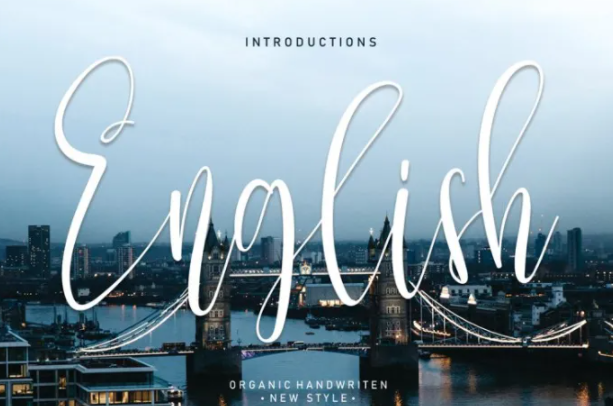
[Fontbundles] English Font (2021)
Популярный и профессиональный шрифт. Современный и элегантный, этот шрифт состоит из красивых креативных штрихов.
Этот шрифт идеально подходит для ваших творческих идей, как формальных, так и неформальных. Он имеет современный стиль с нотками творческих идей, который очень подходит для применения везде, где требуются творческие идеи, например, на пригласительных открытках,
бланки, логотипы сайтов, социальные сети, баннеры, реклама, брошюры, упаковочная продукция, кожаные изделия и любая продукция, требующая написания.
Благодаря использованию этого шрифта все ваши изделия будут выглядеть роскошно, элегантно и привлекательно, попробуйте и убедитесь в этом.
Этот шрифт включает в себя полный набор красивых прописных и строчных букв, цифр, разнообразных знаков препинания и лигатур. Все строчные буквы имеют начало и конец, обеспечивая реалистичный стиль. все, что вы получаете.